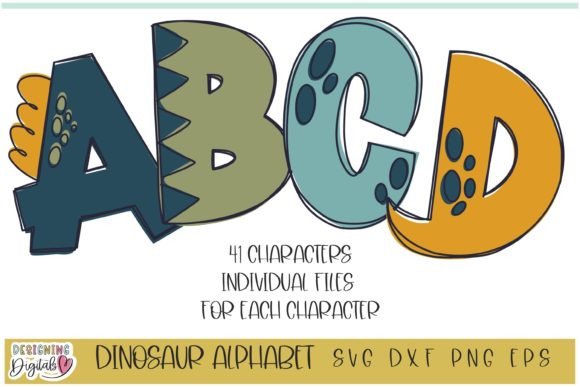
Dinosaur SVG Doodle Letters
Trouver les bons éléments de conception peut être un défi, mais Dinosaur SVG Doodle Letters propose une collection exceptionnelle qui rehausse instantanément votre travail.
Que vous créiez des produits POD (impression à la demande), des invitations de mariage ou des visuels pour les réseaux sociaux, Dinosaur SVG Doodle Letters est un choix idéal.